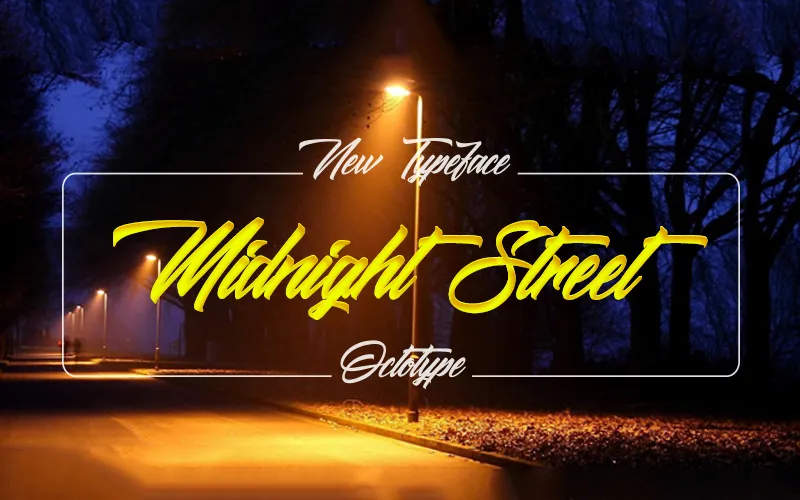
Midnight Street Script Font – Download Grátis
A Midnight Street Script Font é uma obra de arte única que traz à vida uma linguagem sofisticada com uma cara urbana. Criada pelo incrível designer Octotype, essa fonte calligráphica cativa os olhos graças a suas linhas fluidas e textura realista. Seu uso nos permite criar mensagens poderosas no formato de logotipos, selos ou até mesmo em materiais gráficos digitais. Perfeita para projetos que valorizam estilo e originalidade, a Midnight Street Script Font é um excelente investimento tanto para designers quanto para aqueles desejando adicionar um toque único ao seu trabalho. Com o endereço de contato  para obtenção do licenciamento comercial, não hesite em explorar mais esse belo recurso gráfico que revolucionará sua abordagem criativa.